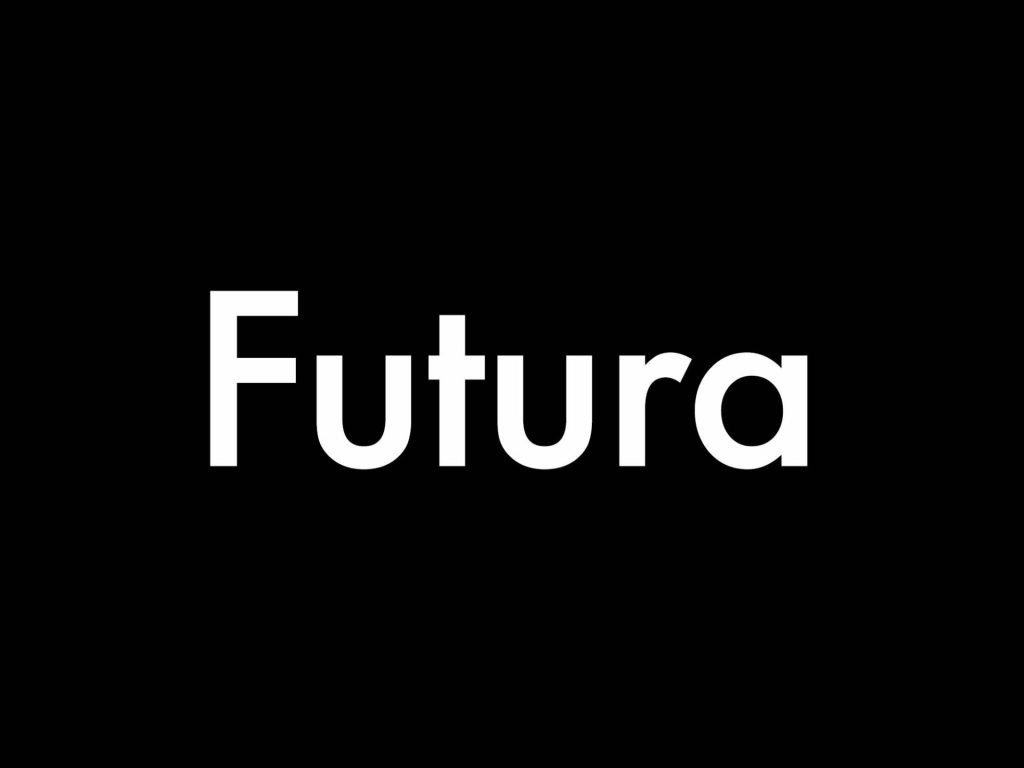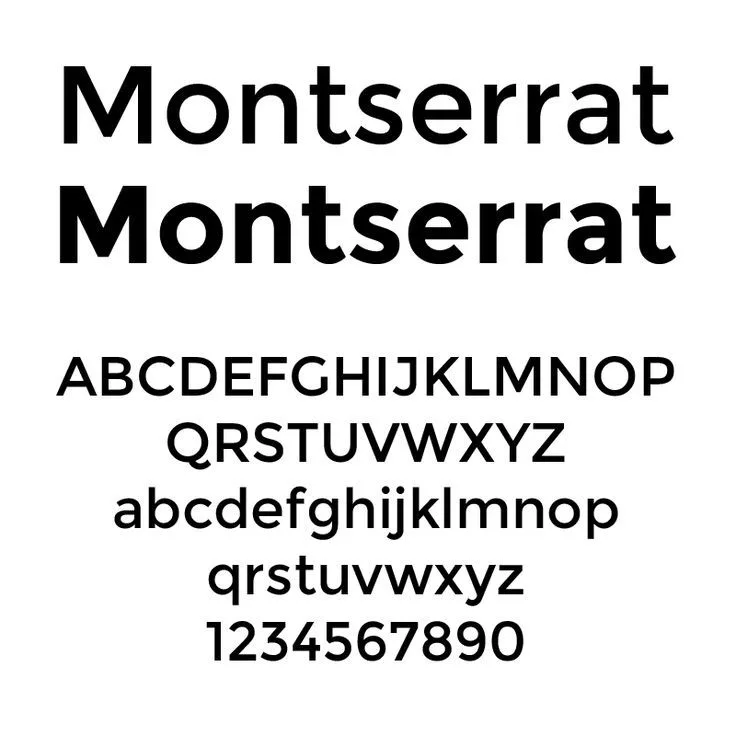
Contoh Font Keren
Untuk pekerjaan formal sehari-hari yang dilakukan dengan Microsoft Word mungkin hanya memerlukan font Times New Roman atau Calibri saja. Namun, lain halnya dengan postingan sosial media yang sangat membutuhkan kreativitas. Banyak contoh font keren yang cocok digunakan pada konten sosial media, yang mana setiap font ini memiliki keunikannya masing-masing.
Saat ini, kira-kira sudah ada lebih dari 200 ribu jenis font yang tersedia dan bisa diakses secara daring. Meskipun memiliki banyak pilihan, hal ini malah menimbulkan kebingungan tersendiri untuk memilih font mana yang paling tepat. Oleh karena itu, MinTiv akan memberikan contoh font keren untuk konten sosial media yang sesuai dengan tipe dan konteks postingannya.
Yuk simak ulasan berikut!
Jenis Font Utama
Jumlah font mungkin sudah menyentuh angka ratusan ribu. Namun, seluruh font tersebut terbagi ke dalam enam kategori utama: Serif, Sans Serif, Slab Serif, Script, Handwritten, dan Decorative. Berikut uraiannya:
• Serif: Font ini memiliki goresan di setiap ujung karakternya, sehingga terlihat elegan dan tradisional. Contohnya adalah Times New Roman dan Georgia.
• Sans-serif: Jenis ini hampir tidak memiliki goresan sama sekali di ujungnya, sehingga terlihat lebih minimalis dan modern. Contohnya adalah Arial dan Helvetica.
• Slab serif: Cenderung terlihat lebih tebal dari font lain, hingga sering dipersepsikan sebagai simbol kekuatan dan stabilitas. Contoh yang paling terkenal adalah Rockwell.
• Script: Font ini meniru tulisan huruf sambung atau kaligrafi yang terlihat elegan dan memiliki elemen personal. Contohnya adalah Brush Script dan Lucida Calligraphy.
• Handwritten: Sesuai namanya, font ini meniru tulisan tangan manusia yang terlihat alami, unik, dan penuh ketidaksempurnaan.
• Decorative: Font ini adalah yang paling bergaya dan biasanya menyesuaikan dengan tema yang ada untuk kebutuhan kreatif. Contohnya adalah Chiller dan Comic Sans.
Contoh Font Keren
Setelah mengetahui jenisnya, lantas font apa saja yang paling cocok untuk sosial media? Cari tahu jawabannya berikut ini:
1. Montserrat
Montserrat
Montserrat adalah salah satu font Sans Serif yang paling serbaguna karena desainnya yang modern dan bersih. Font ini tetap terlihat cocok baik tipis, hitam tebal, hingga dalam bentuk italic. Bentuk katanya juga sangat seimbang dan geometris, tapi terlihat sederhana. Hal tersebut membuat Montserrat sangat cocok untuk desain UI atau desain branding pada konten sosial media.
Selain itu, Montserrat juga sangat mudah untuk diakses, sehingga font ini merupakan salah satu yang paling populer. Banyak desainer yang menyukai font ini karena mudah dibaca dan memiliki estetika sekaligus.
2. Didot
Didot
Didot dikenal akan elegansinya karena memiliki kontras yang tinggi antara goresan tebal-tipis, garis melingkar, dan secuil font Serif. Orang yang membaca font ini seakan-akan diajak naik rollercoaster karena desainnya. Walau demikian, Didot memancarkan kesan yang canggih dan berkelas. Dengan kontras yang terlihat dramatis, Didot dapat menambah kesan yang fashionable pada brand apapun.
Maka tak heran jika kebanyakan brand fesyen ternama seperti Zara dan Giorgio Armani cenderung menggunakan font ini. Bahkan dalam kebanyakan iklannya, brand-brand tersebut menggunakan Didot untuk menyampaikan kesan berkelas, stylish, dan kedewasaan.
3. Futura
Futura
Kalau font sebelumnya cenderung modern atau elegan, tapi apakah ada font yang terlihat klasik tapi tetap keren? Jawabannya ada, yaitu Futura! Font ini sudah ditemukan sejak tahun 1920an oleh desainer jerman yang bernama Paul Renner. Saat ini, font Futura dianggap klasik dan tetap relevan
Tulisannya ditandai dengan lebar goresan yang rata, bentuk geometris yang unik, serta tidak memiliki unsur serif sama sekali. Ciri-ciri tersebut membuat Futura sebagai pilihan yang ideal untuk desain konten brand yang bergaya klasik atau vintage.
4. Helvetica
helvetica
Selain Montserrat, Helvetica merupakan salah satu font Sans-serif paling ikonik. Secara sekilas, font ini memang terlihat netral dan mudah dibaca. Elemen dekoratifnya pun terbliang sangat minim, sehingga menunjukkan kesan yang tegas dan jelas.
Oleh karena itulah kepopuleran Helvetica menyebar ke berbagai industri, khususnya untuk branding dan desain digital. Font ini juga memiliki adaptabilitas tinggi jika dipadukan dengan font lain. Beberapa brand seperti American Apparel dan Toyota bahkan menggunakan font ini pada logonya.
5. Juvenile
Juvenile
Jika ada yang ingin kontennya dihias dengan font Handwriting, maka Juvenile adalah pilihan yang cocok. Diciptakan sejak tahun 1950an, Juvenile membawa kesan nostalgia tersendiri. Font ini juga sangat serbaguna baik yang original maupun tebal. Bahkan, fontnya juga kompatibel dengan format TTF, OTF, dan WEB. Juvenile sangat cocok digunakan pada flyer, postingan Instagram, story, dan konten ala-ala vintage lainnya.